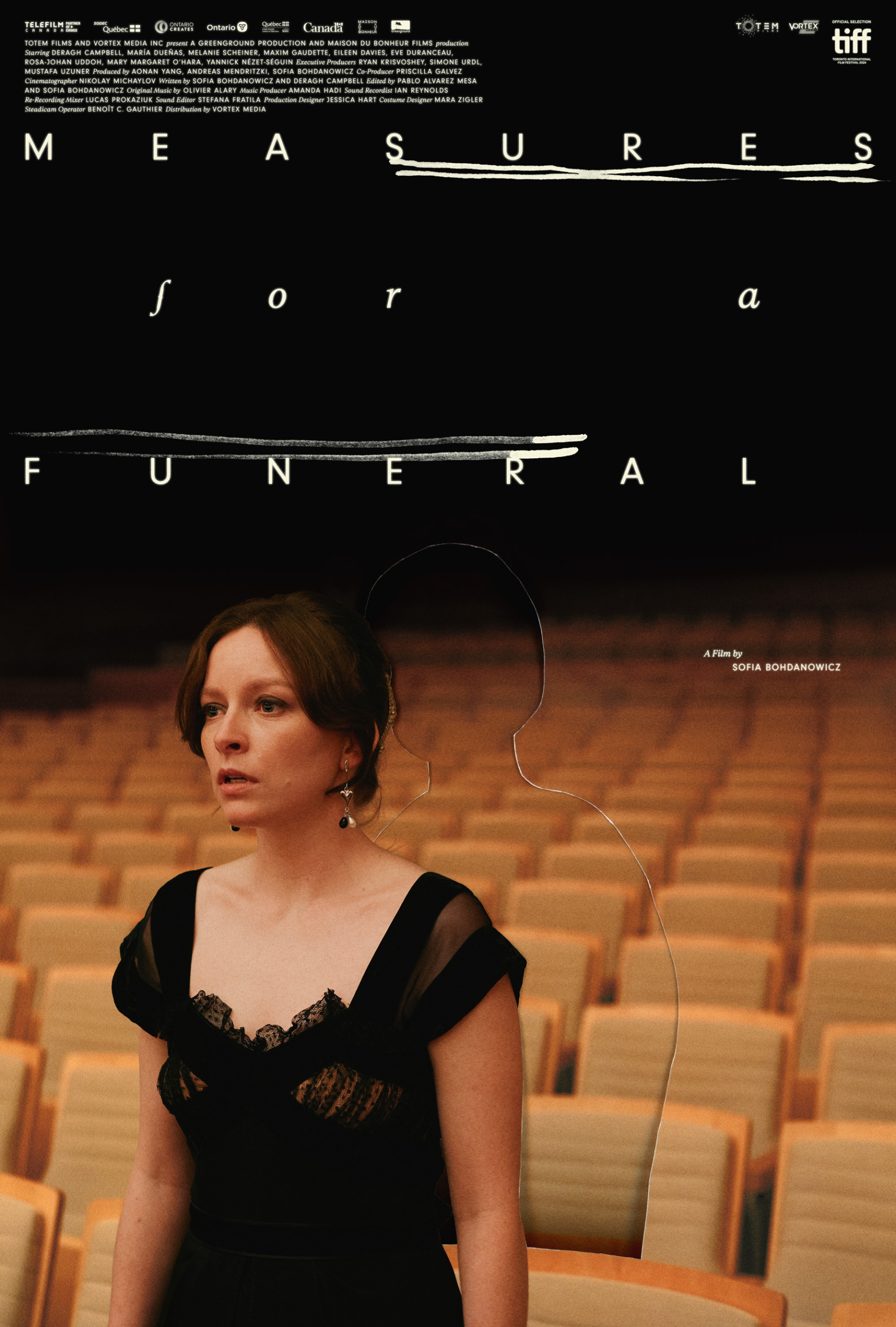
Measures for a Funeral
Measures for a Funeral beleuchtet auf brillante Weise die Annäherung einer jungen Akademikerin an eine Frau — die gefeierte kanadische Geigerin Kathleen Parlow aus dem frühen 20. Jahrhundert — während sie gleichzeitig vor einer anderen flieht, ihrer gescheiterten Musikerin Mutter.
Der grobe Ausschnitt spricht vom Leitmotiv der Händen im Film. Dies zeigt sich auch in der Titelgestaltung, das wie Musiknotationen, handgeschriebene Notizen oder Geigensaiten wirkt.
Schrift: Rhetorik Serif von AllCaps & Neuzeit Grotesk von Wilhelm Pischner